mojimo(モジモ)」シリーズに第2弾製品「mojimo-kirei(文字も綺麗)」「mojimo-kawaii(文字も可愛い)」「mojimo-oishii(文字も美味しい)」3製品が登場
フォントワークスは2018年8月28日よりフォントサービス「mojimo(モジモ)」の第2弾製品として「mojimo-kirei(文字も綺麗)」「mojimo-kawaii(文字も可愛い)」「mojimo-oishii(文字も美味しい)」の3パックを同時リリースした。
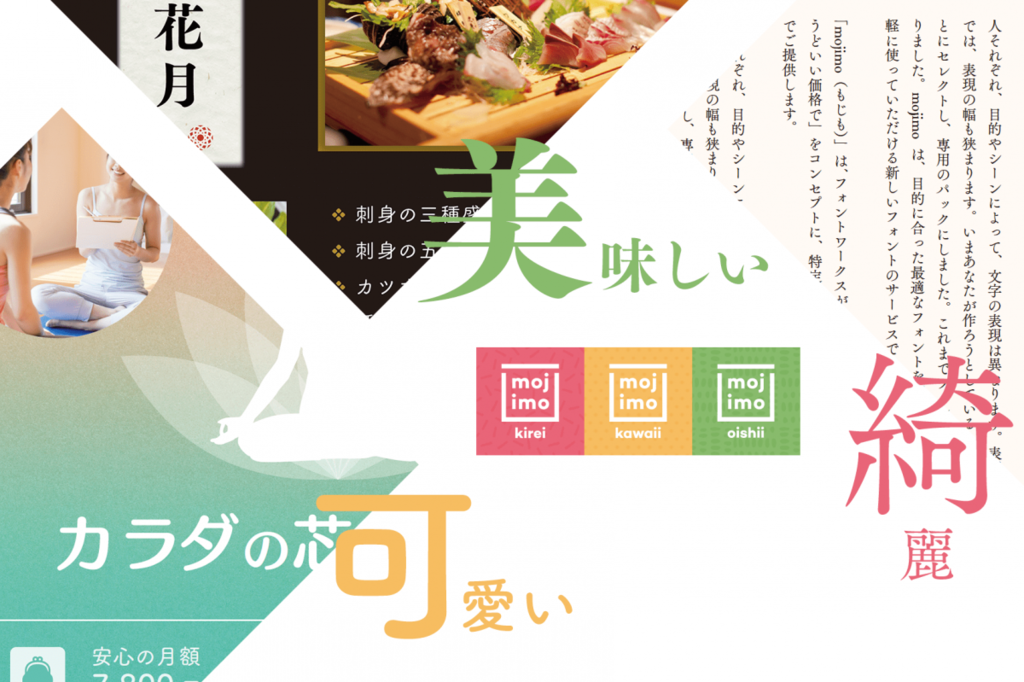
mojimo-kirei
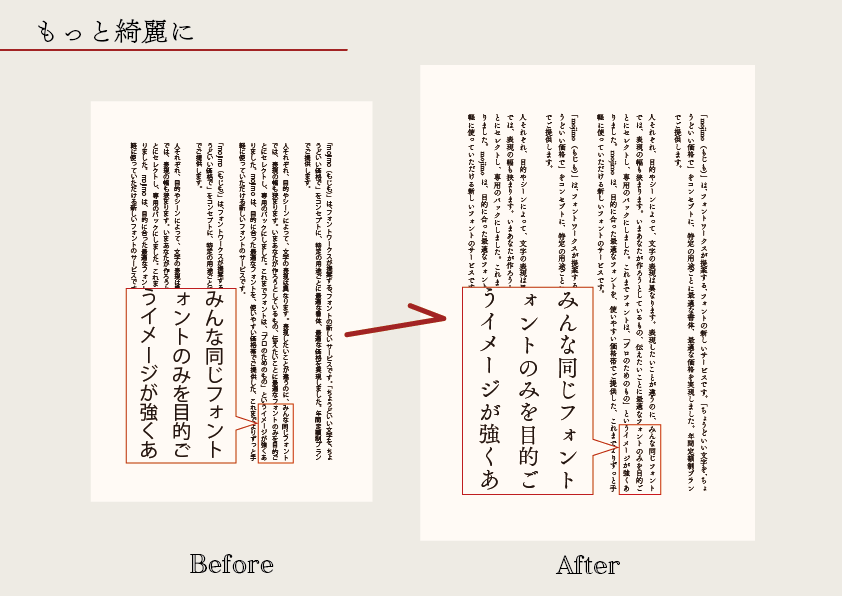
筑紫明朝、筑紫オールド明朝、筑紫アンティーク明朝をはじめとした、フォントワークスのフォントの中でも上品さや綺麗さを表現した書体を収録した8書体パック。
上品さや読みやすさを重視する制作物に適している。
▼mojimo-kirei収録フォント
筑紫明朝-LB
筑紫B明朝-L
筑紫オールド明朝-R
モード明朝Bラージ-L
筑紫アンティークS明朝-L
筑紫ゴシック-L
筑紫A丸ゴシック-M
クレー-M
mojimo-kawaii
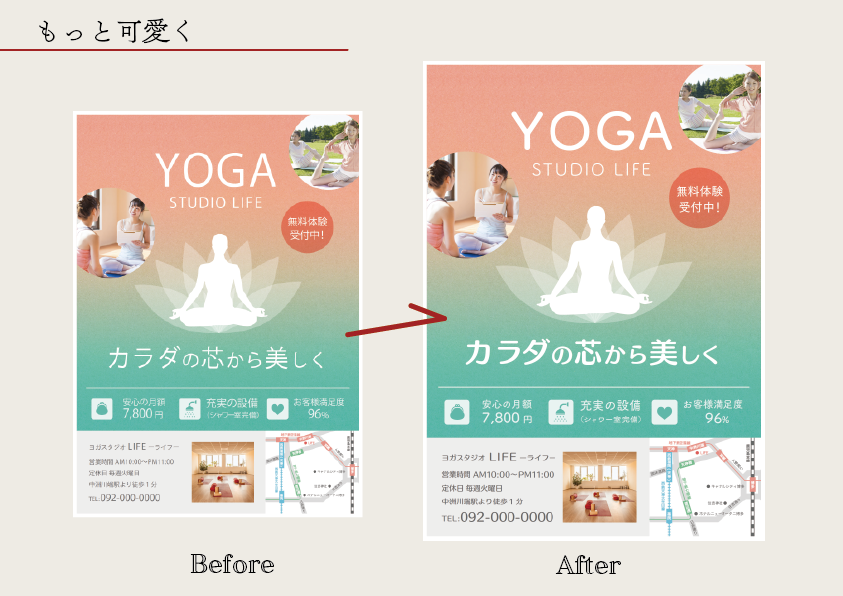
筑紫ゴシック、筑紫オールドゴシックなど文字のデザインが可愛らしく読みやすいゴシック体を中心として明朝体や綺麗めなデザイン系フォントの8書体パック。
可愛らしい雰囲気を表現しながらも、読みやすさやポイントで使いたいときなどに適している。
▼mojimo-kawaii収録フォント
マティス-L
モード明朝Aラージ-R
スキップ-D
ハミング-D
セザンヌ-DB
筑紫ゴシック-D
筑紫オールドゴシック-B
筑紫A丸ゴシック-D
mojimo-oishii
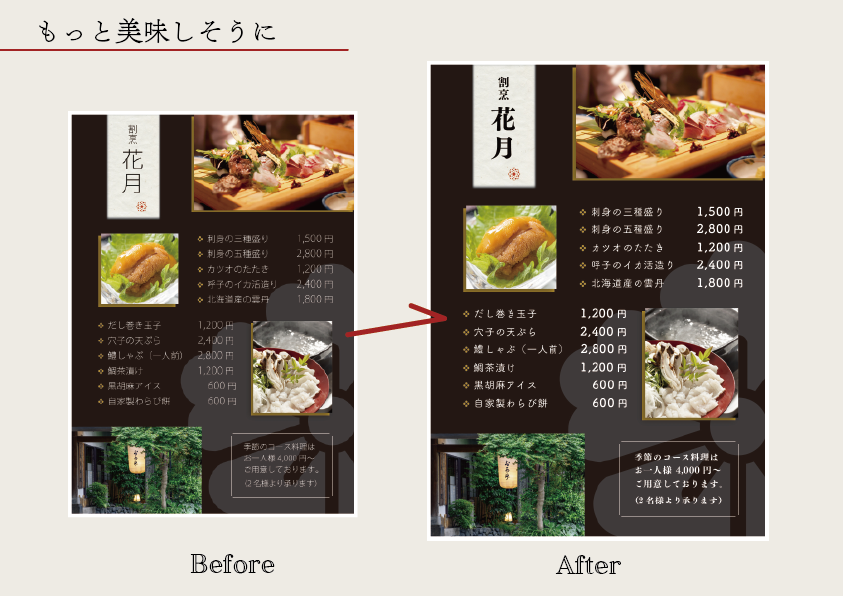
筑紫Cオールド明朝や筑紫B見出ミンなど、使用するだけで「美味しそうな味わい豊かな」情景を表現できる、ゴシック体・明朝体をバランスよく収録したフォントパック。ウエイトも太めの書体から細めの書体までご用意しており、キチンと感も少し崩した感じもどちらも表現でき、初めて制作をされる方などにも適している。
▼mojimo-oishii収録フォント
UD角ゴ_ラージ-E
筑紫アンティークLゴシック-B
筑紫Cオールド明朝-R
モード明朝Bラージ-B
筑紫B見出ミン-E
マティスV-M
UD丸ゴ_ラージ-DB
筑紫B丸ゴシック-B
mojimo(モジモ)シリーズ第1弾「mojimo-manga」
フォントワークスは、特定の用途やシーン、利用者に最適な書体をセレクトし、最適な価格で提供する新フォントサービス「mojimo(モジモ)」を発表した。
mojimo(モジモ)は、「ちょうどいい文字を、ちょうどいい価格で」をコンセプトに、「文字」も、もっと身近に、「文字」も、もっと大事に、「文字」も、もっとこだわってほしいそんな想いから生まれたフォントサービス。
プロデザイナー向けだったフォントを目的に合った最適なフォントをリーズナブルな価格で提供していく、これまでよりずっと手軽に使っていただける新しいフォントサービス。
第1弾として「mojimo-」サービスとして、同日の3月1日に発表された「mojimo-manga」に続き、今後も新プランが追加で発表されていきそうだ。
第2弾製品、第3弾のプランはどうなるのか、今後もmojimoに期待したい。
人気マンガや人気アニメの公式フォント36書体がちょうどいい価格で使えるmojimo第1弾サービス「mojimo-manga(モジモマンガ)」
mojimo第1弾サービスとして、2018年3月1日(木)より、人気アニメ公式フォントを含む、同人誌制作に最適な書体をセレクトした「mojimo-manga(モジモマンガ)」の提供を開始することを発表した。
フォントワークスのフォントラインナップの中でも人気アニメ公式フォントをはじめとしたアニメやコミックなどでの利用頻度の高いフォント、また明朝体やゴシック体などのスタンダードなフォント、デザイン系フォントまでを揃えた36書体をセレクト。ダウンロード形式のフォントサービス。